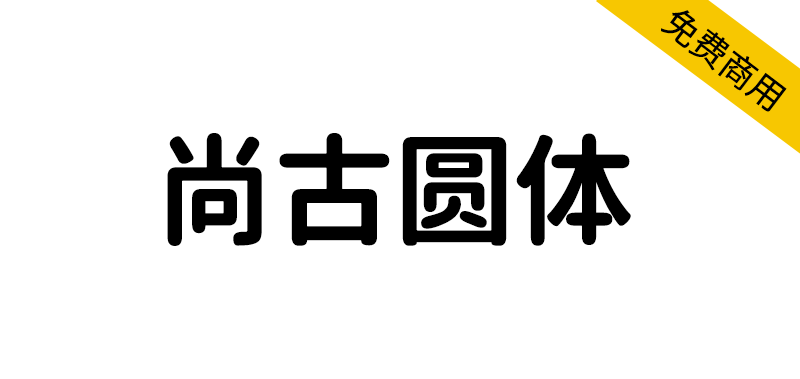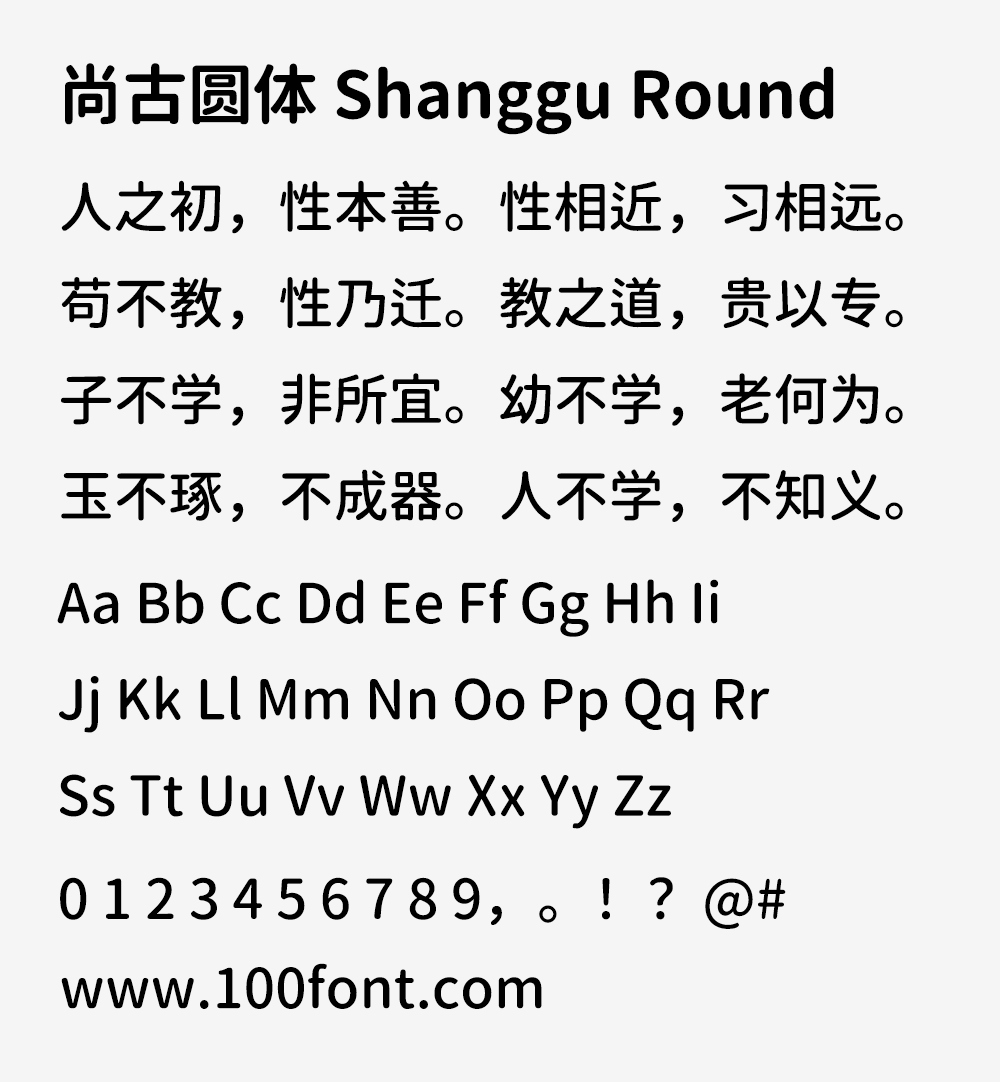
尚古字体是一套泛中日韩传承字形(旧字形),基于思源黑体、思源宋体、思源等宽以及思源系列衍生字型制作,包含黑体、明体、圆体、等宽以及简转繁字型。
说明1:新旧异体字(如青-靑尚-尚兑-兑温-温等)合并为旧字形。
说明2:新旧异体字遵从Unicode分开编码,根据地区标点和简体字的不同,分为TC、SC、JP三种,字体名称中的TC、SC、JP仅代表地区标点的不同,本字体不使用地区的字形标准。
说明3:简转繁体,简入繁出的字体,可根据文字属性动态匹配一简多繁的情况(简转繁的意思就是输入简体字时会自动转换成繁体字)